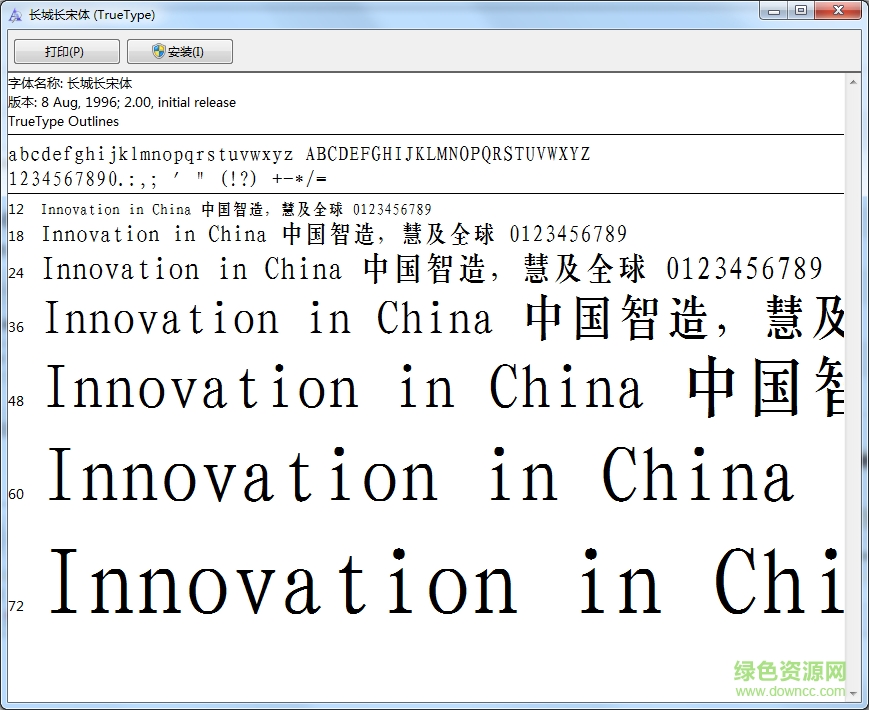
长城长宋体
长城长宋体是一款非常工整的长城字体,由于结合了宋体的元素,字体看起来非常的清新自然,字体整体偏细长,支持中文、英文和阿拉伯数字,欢迎有需要的朋友到绿色资源网下载使用!
官方介绍
长城长宋体笔画有粗细变化,而且一般是横细竖粗,末端有装饰部分(即“字脚”或“衬线”),点、撇、捺、钩等笔画有尖端。